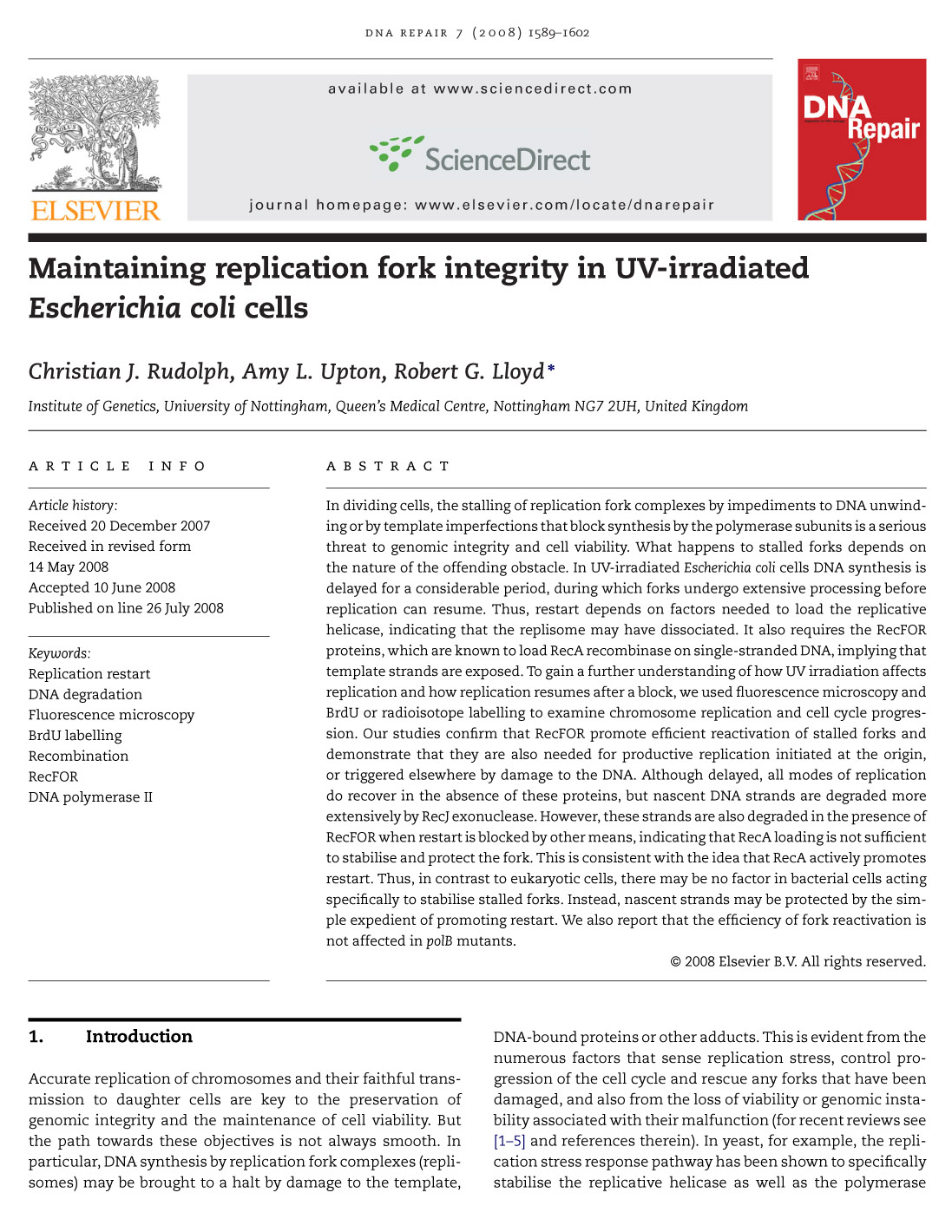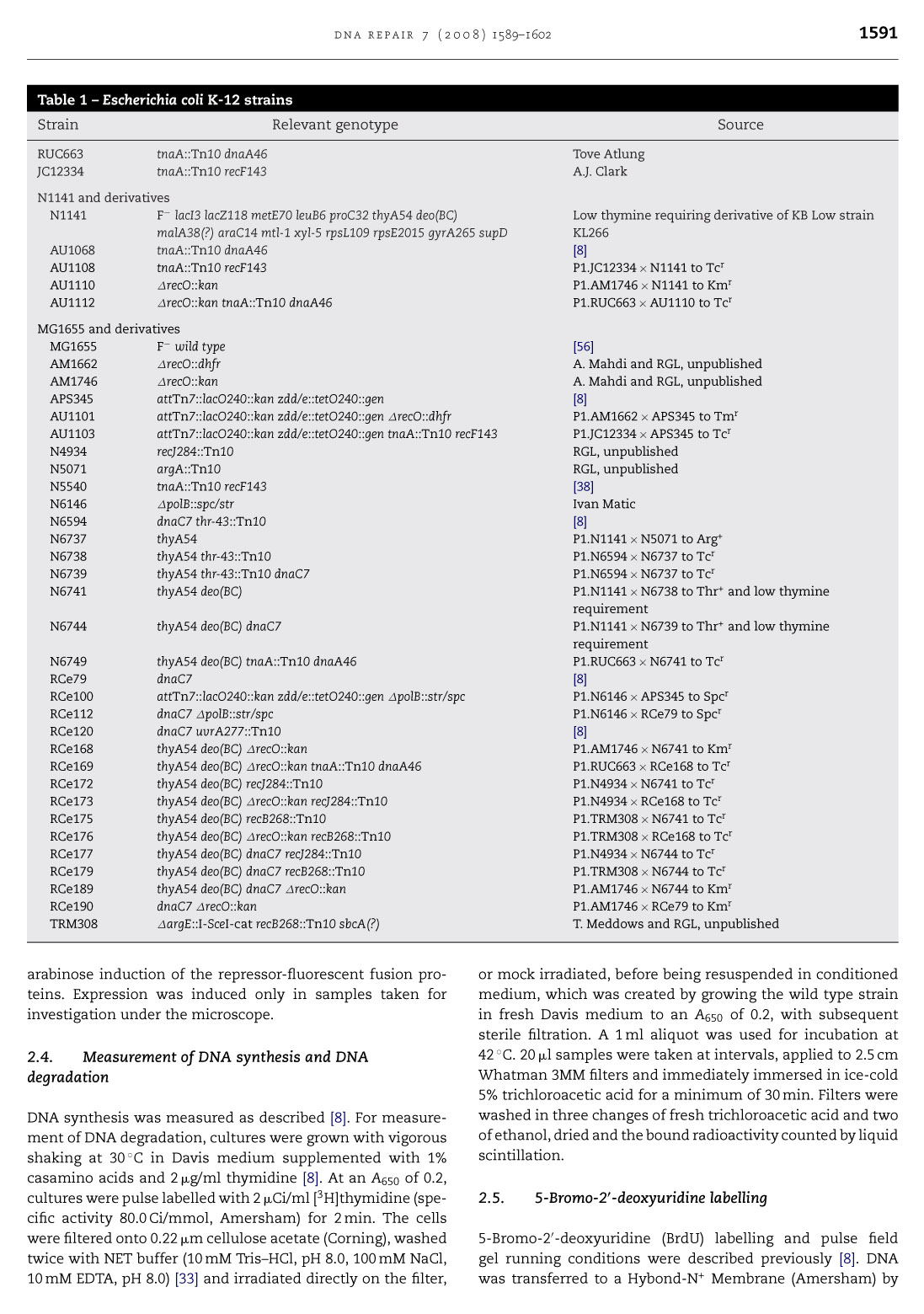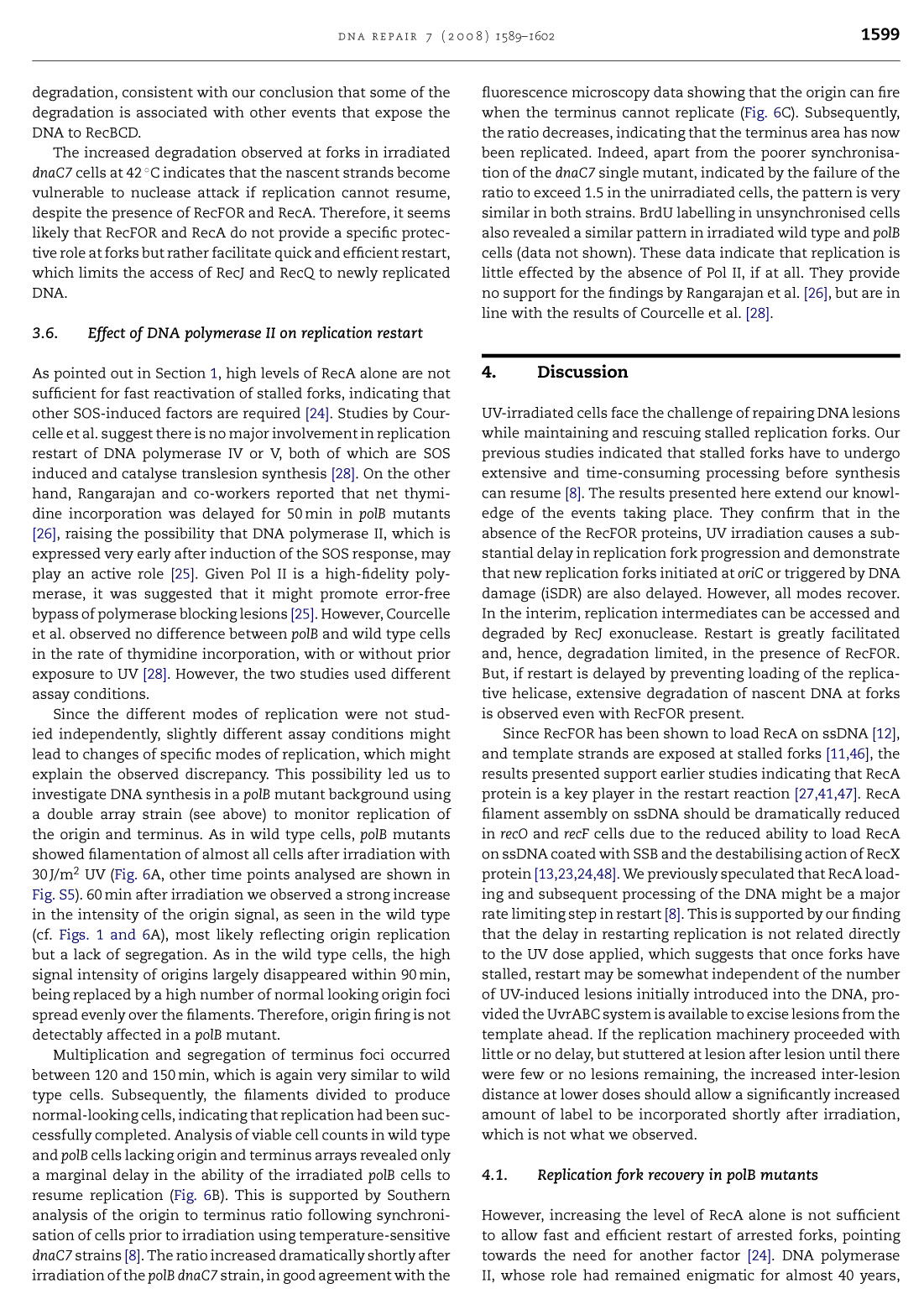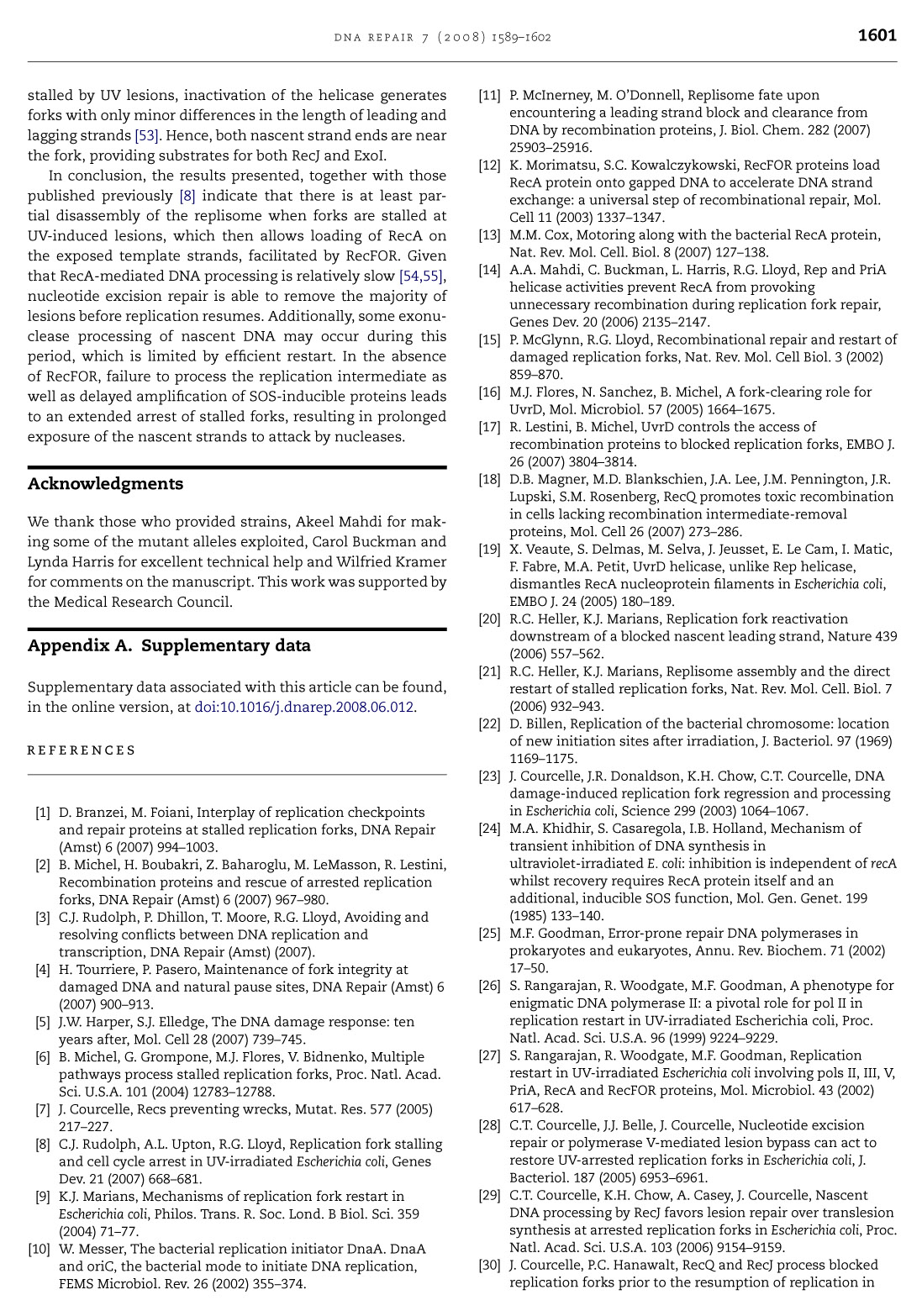
Schrift für medizinische Arbeit
Ich suche eine Textschrift für eine medizinische Arbeit zum Thema Schwerionen-Strahlentherapie. DIN A4, zweispaltig, etwa 150 Seiten.
Die Schrift sollte frisch und modern wirken, aber auch wissenschaftlich-sachlich. Zielgruppe: medizinische Fachleute.
Mathematische Zeichen und griechische Buchstaben wären gut.
Schriften, die ich mir schon angeschaut habe:
• Comenia: nicht schlecht, ß aber grauenvoll[/*:m:1ty03p09]
• Expo Serif: gefällt mir gut, der dreieckige i-Punkt stört aber, und der überragende f-Bogen bewirkt Löcher vor Buchstaben mit Oberlänge[/*:m:1ty03p09]
• Lido: seltsames ß[/*:m:1ty03p09]
• Stuart: ein bißchen zu dynamisch[/*:m:1ty03p09]
• Leitura: abenteuerliche Zurichtung[/*:m:1ty03p09]
• DTL- und TEFF-Schriften: zu teuer[/*:m:1ty03p09]
Schrift-Klassiker habe ich viele lizenziert, möchte die ja aber gerade nicht verwenden, sondern mal eine neuere Schrift. Habt ihr also noch ein paar Geheimtipps für mich? :?
In der Welt der Fachzeitschriften sind die Mediziner vergleichsweise konservativ. Eben traditionelle Textschriften.
Wie wäre es mit der Caecilia, die Minimalist schon im anderen »Medizin-Thread« vorgeschlagen hat? Wie schon dort gesagt, »DNA Repair« von Elsevier hat das einige Jahre gemacht und ich fand das ging sehr gut. Bei Bedarf kann ich gerne mal eine Seite einstellen.
Fedra Serif ist vermutlich zu teuer? Wie wäre es mit der ITC Slimbach? Oder, wenn es etwas kantiger sein soll, mit der Warnock Pro? Die ist natürlich super ausgebaut und noch relativ selten zu sehen. Wenn es serifenlos sein soll: hat die Foundry Form Griechische Buchstaben? Die Uni Nottingham hat die im CD und ich finde sie jeden Tag wieder modern, schick und trotzdem vertrauenerweckend.
P.S.: Was gefällt Dir denn ausgerechnet an der Zurichtung der Leitura nicht? Ich habe alle möglichen Vorbehalten gegen diese eigentlich schöne Schrift; die Zurichtung hat nie dazu gehört ... :?
Wie gefällt dir denn Premiera von den Typejockeys? (Okay, das Stichwort mathematisch/griechisch hab ich überlesen … :party: )
Falls griechisch wichtig ist, würde ich zum Schmied gehen und nicht zum Schmiedl: Parachute
Minion Math bietet Typoma.
Andron Mega von Andreas Stötzner, die könntest du sogar zuvor ausprobieren.
Meine Erfahrung mit medizinischen Kollegen und Naturwissenschaftlern zeigt durchgängig eine äußerst geringe Empfindlichkeit im Hinblick auf typographische Stilfragen. Was wir (Mediziner, Physiker usw.) in fachlichem Bezug lesen, lesen wir oft, weil wir müssen. Wenn wir es gerne und mit Genuss lesen, dann wegen des Inhaltes. Am liebsten und mit dem größten Genuss lesen die meisten übrigens eigene Werke :D :lol:
Mir persönlich (aber ich bin nicht typisch) ist das Vorgehen von Verlagen in dieser Hinsicht nicht immer nachvollziehbar und freue mich sehr, wenn hier engagiert nach passender Schriftauswahl für diese Zielgruppe gefragt wird.
Die meisten von mir befragten Betroffenen haben sich über typographische Fragen noch nie Gedanken gemacht, keinerlei diesbezügliche Beobachtungen registriert und sich bei eigenen Veröffentlichungen blind den Vorgaben anderer (Dekanate, Kommissionen, Verlage etc.) gebeugt.
Das Gute : Ein "der Kunde will das aber so" wird da eher selten sein....
Die Caecilia könnte ich mir vielleicht vorstellen, bin aber noch unsicher, ob eine Egyptienne nicht zu ungewöhnlich wäre. Es wäre gut, Christian, wenn Du mal eine Beispielseite hochladen könntest.
Die Fedra Serif (B) und die Premiera werde ich mir mal genauer anschauen. Auch die Centro Serif sieht auf den ersten Blick nicht schlecht aus.
Die Slimbach gefällt mir nicht so, die Warnock scheint mir etwas zu kantig zu sein.
Eine Grotesk will ich nicht für den Text verwenden. Statt der Foundry Form Sans wäre aber die Form Serif sicher nicht schlecht, wohl aber zu teuer.
Minion und Andron sind mir zu klassisch.
Jupp! :lol:
Bei meiner Anmerkung zur Zurichtung der Leitura meinte ich die Kursive:
Das sieht doch schrecklich aus! :shock:
Die Caecilia könnte ich mir vielleicht vorstellen, bin aber noch unsicher, ob eine Egyptienne nicht zu ungewöhnlich wäre.
:huhu: Ich kann Dir aus eigener Erfahrung berichten, dass die Eingewöhnungszeit vernachlässigbar kurz ist; nach wenigen Sekunden tarnt sich die Caecilia sehr erfolgreich als gutaussehende Serifenschrift und fällt dann nicht mehr auf :D PN mir mal Deine E-Mail-Adresse, dann schick ich Dir heut Nachmittag ne grobe Beispielseite :D
Da ich nicht genau weiß was Du brauchst hier mal vier typische Anwendungen aus dem wissenschaftlichem Bereich (Titel, Tabelle, Fließtext und Literaturverzeichnis):
Danke für die Bilder, Christian!
Die Leitura sieht bei Dir wirklich wesentlich besser aus als in der MyFonts-Vorschau (wohl wegen Unterschneidung?), wenn auch noch nicht vollkommen: ich sehe da immer noch pr ac he. Ich finde allerdings, daß die Zurichtung der Leitura News noch etwas besser aussieht. :?
Sonst gefällt mir die Leitura schon ziemlich gut, und Deinen bisherigen Berichten nach ist sie ja auch (von gewissen Mängeln abgesehen) recht brauchbar. Schade, daß ich damals bei dem günstigen Paket nicht zugeschlagen habe!